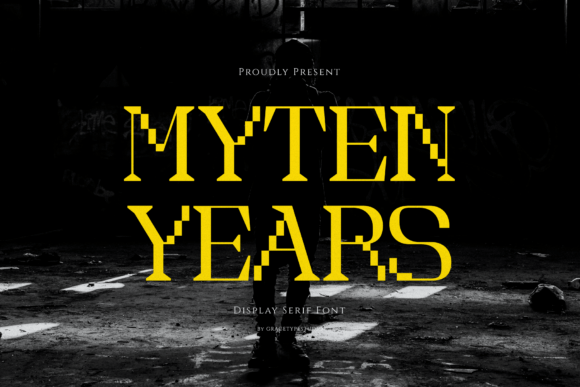
Myten Years
Myten Yearsのような高品質の素材をお探しの場合、このプレミアムパッケージはクリエイティブなプロジェクトに素晴らしい選択です。
精密に作られたMyten Yearsは、クリーンなベクター、滑らかなタイポグラフィ、そして安心のための商用ライセンスを提供します。
POD(オンデマンド印刷)製品、結婚式の招待状、またはソーシャルメディアのグラフィックを作成している場合でも、Myten Yearsは理想的です。